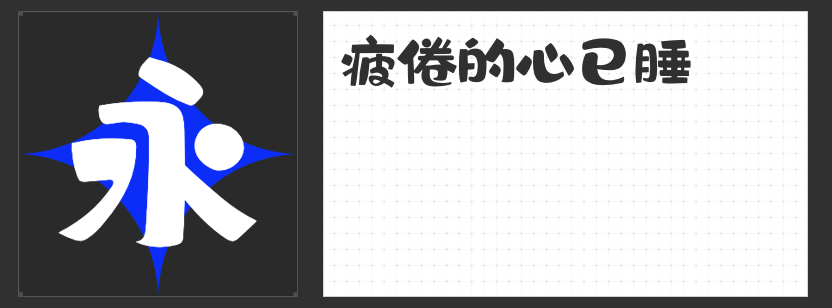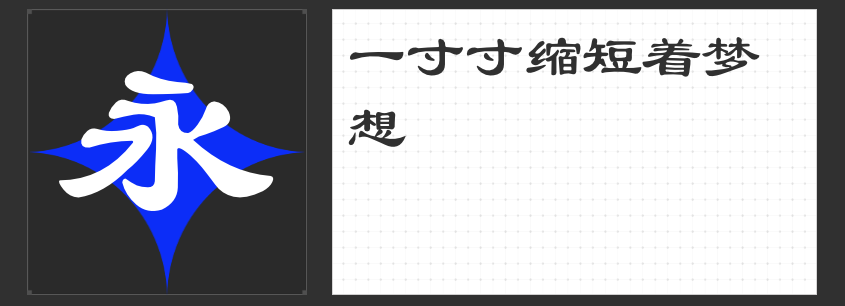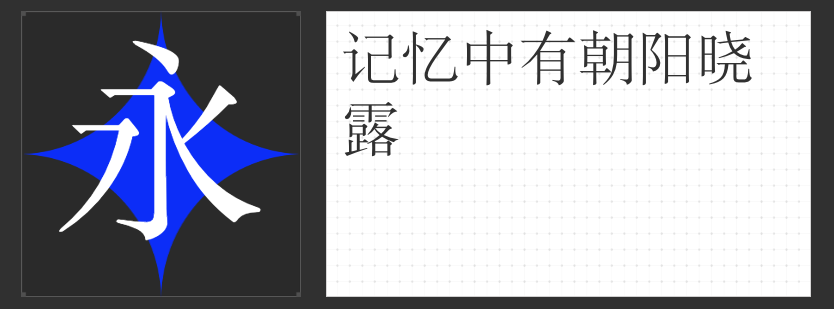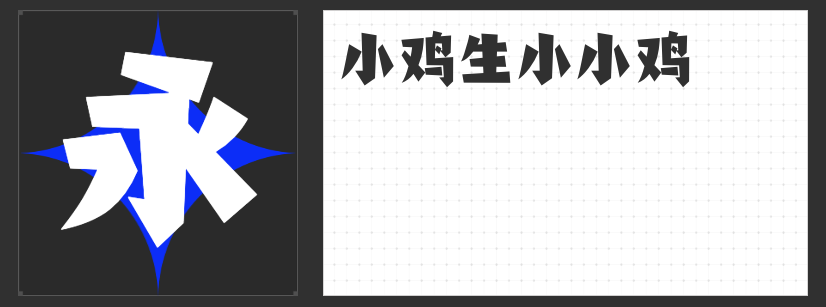
童趣无限:四大字体点亮儿童读物设计
在儿童教育与知识传播的广阔天地里,字体的选择不仅关乎视觉美感,更直接影响到孩子们的阅读兴趣与理解力。今天,我们特别推荐四款专为儿童教材与知识书籍设计的字体,它们各具特色,旨在为孩子们打造一个既有趣又高效的阅读环境。
1.励字憨憨简
这款字体以其圆润可爱的形态,非常适合用于儿童书籍的标题和封面设计。憨态可掬的笔画,仿佛能瞬间吸引孩子们的注意力,激发他们的探索欲,让每一次翻开书本都成为一次愉快的旅程。
2.励字俊林简
作为封面与插图的绝佳搭档,励字俊林简以其简洁而不失优雅的线条,为书籍增添了一抹清新脱俗的气息。它既能凸显书籍的主题,又能与丰富多彩的插图和谐共生,共同讲述一个个生动有趣的故事。
3.励字隶书简繁
对于介绍类标题、正文标题以及涉及古代知识的部分,励字隶书简繁无疑是最佳选择。它融合了传统隶书的韵味与现代简化的便捷,既保留了古典文化的精髓,又便于孩子们阅读和理解,让古代智慧以更加亲切的方式走进孩子们的世界。
4.励字书宋简繁
正文与介绍内容的呈现,则非励字书宋简繁莫属。这款字体借鉴了宋体的端庄与书法的韵味,同时进行了简化处理,使得文字既清晰易读,又不失文化底蕴。它能够帮助孩子们在轻松愉快的氛围中,深入探索知识的海洋。
总之,这四款字体各具特色,共同为儿童教材与知识书籍的设计提供了丰富的选择。我们相信,通过它们的运用,定能为孩子们带来更加丰富多彩、生动有趣的阅读体验。